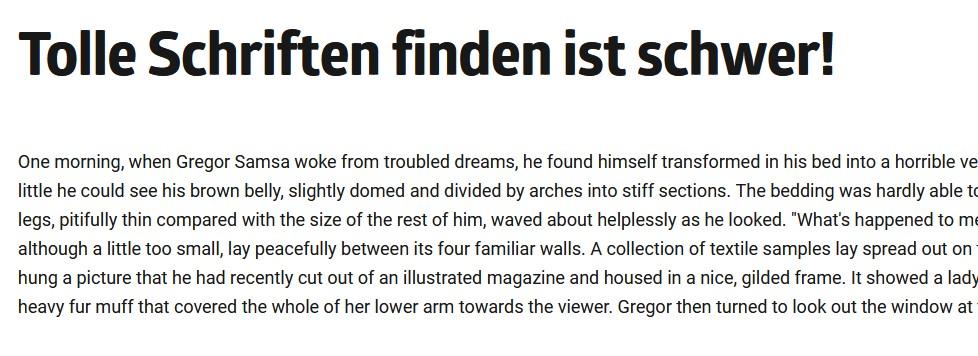
Geeigente PC Schrift (Webfont) erkennen
Hallo, gibt es für "Laien" neben der Beschreibung die Möglichkeit zu erkennen, ob eine Schrift für das Lesen auf Bildschirmen besonders geeignet ist? Manche Schriften Werben ja extra damit. Ein Beispiel: Die Glober TM (https://www.myfonts.com/fonts/font-fabric/glober) wirbt damit, besonders gut für PC und MAc geeignet zu sein. Ich finde aber, die Core Sans NR (https://www.myfonts.com/fonts/s-core/core-sans-nr/) ist angenehmer zu lesen und sieht im Fließtext besser aus. Ist das jetzt nur mein Eindruck? Auf welche Details sollte ich ahchten, eine Schrift als Webfont einzusetzen (neben dem persönlichen Empfingen)?
Manche Schriften werben ja extra damit.
Wenn nicht dabei steht, wodurch diese besondere Eignung erreicht wird, kannst du das m.E. getrost als Marketinggeschwurbel ignorieren.
Lies dich mal in das Thema Font-Hinting ein. Das ist einer der wichtigsten Faktoren, was die Bildschirmdarstellung in kleinen Größen angeht. (Ich empfehle auch den englischsprachigen Artikel, der einen leicht anderen Fokus und bessere Beispiele hat.)
Probleme durch fehlendes oder mangelhaftes Hinting verschwinden allerdings, wenn Fonts hinreichend groß dargestellt werden. Für plakativ große Überschriften spielen Hinting und Antialiasing praktisch keine Rolle. Da kannst du dich auf dein Auge verlassen, ohne groß auf sehr vielen Plattformen testen zu müssen.
Vielleicht könnte ja das ein Tipp für Anfänger sein: Setze Webfonts für sehr große Schriftgrade ein (da ist ja auch die Wirkung am größten). Bei Textgrößen bist du mit Systemschriften auf der sicheren Seite. Alles andere erfordert einiges an Erfahrung.
Darf ich nach deiner Meinung fragen, wie du die Glober findest? Könnte man die gut mit der Roboto kombinieren? https://www.fontfabric.com/fonts/glober/#font-tester
p. s. Kennt jemand ein gutes Online-Tool für "Hinting-Tests"?